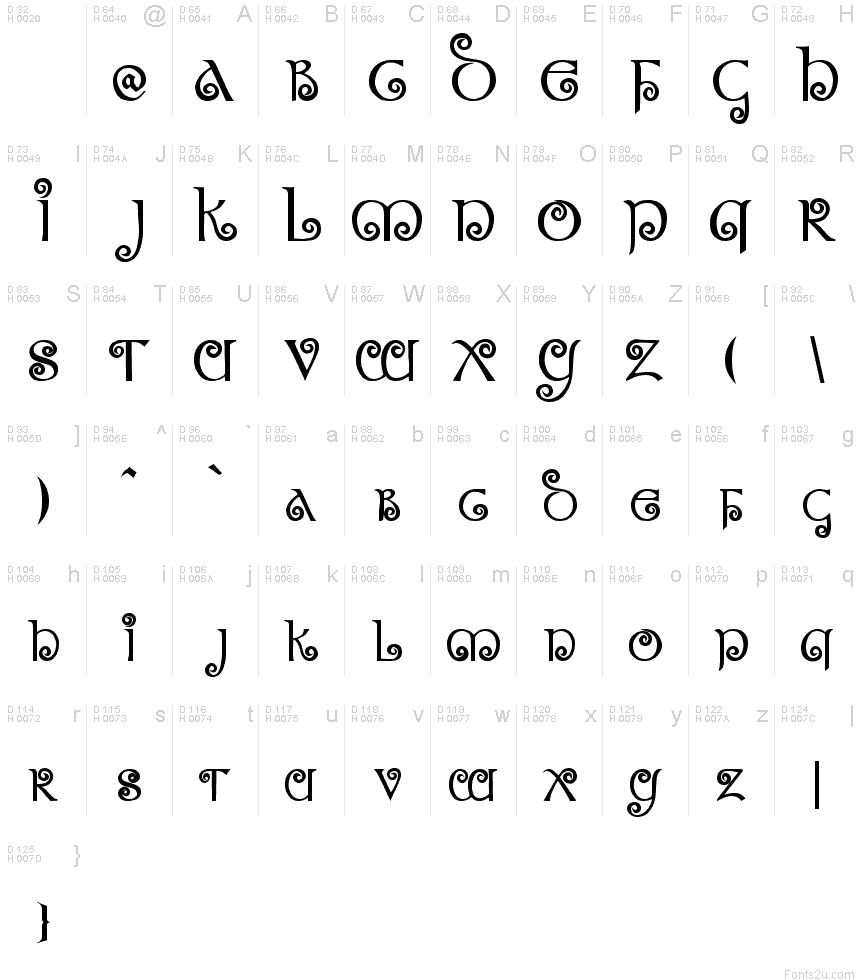
Morgow autorstwa Davida F. Nalle to darmowy, ozdobny krój pisma typu display, wyróżniający się szerokimi, zaokrąglonymi liniami i spiralnymi formami wkomponowanymi w wybrane litery. Kształty sprawiają wrażenie rysowanych ręcznie i ornamentalnych, a zakręcone końcówki i pętelki nadają projektowi baśniowy, średniowieczny klimat.
Morgow to darmowy font, który świetnie sprawdzi się na plakatach fantasy, okładkach książek, zaproszeniach, w logotypach, ozdobnych tytułach oraz opakowaniach tematycznych. Dzięki wyrazistym zawijasom, które przejmują rolę głównego elementu wizualnego, krój ten jest idealny do projektów, w których liternictwo ma pełnić funkcję graficznego akcentu, a nie tekstu użytkowego.